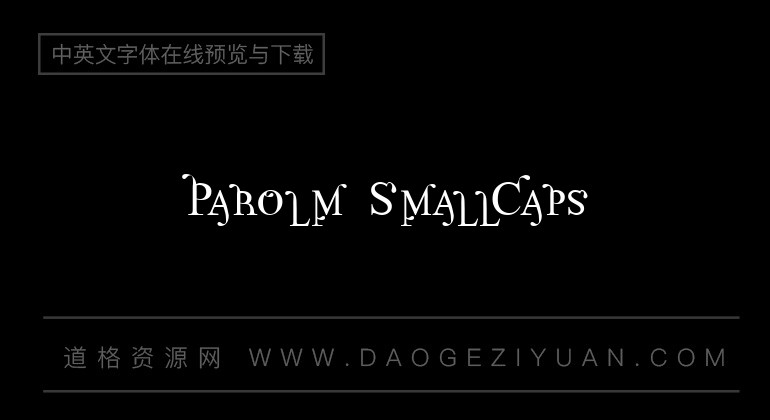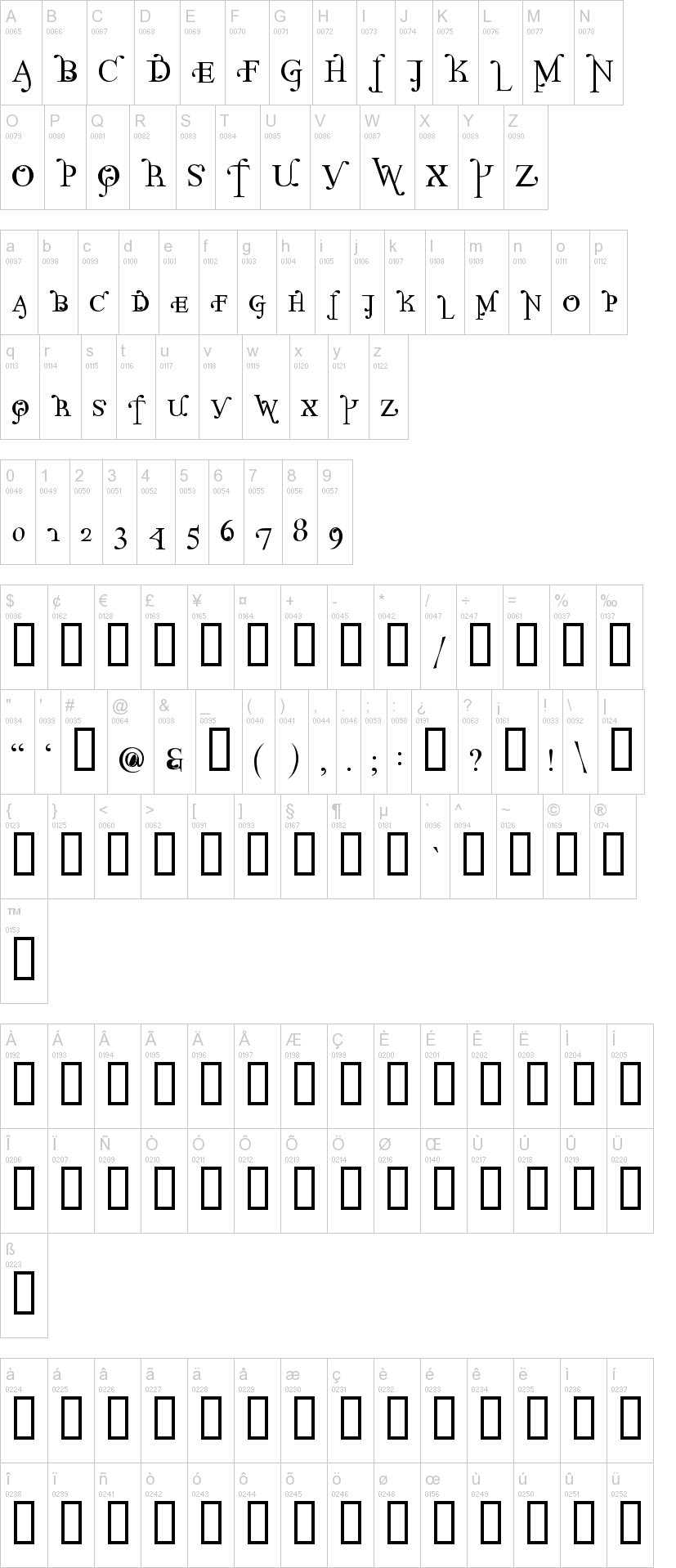
Parolm SmallCaps 是一款简洁优雅的小型大写字体,由 Parolm 公司设计和发布。它的设计灵感来自于经典的报纸字体,在现代化的设计中,它保留了传统的风格,同时具有更加现代的视觉效果。它的字形设计细腻,字重均匀,笔画细腻,给人一种清新舒适的感觉。Parolm SmallCaps 字体可以用于各种文字的设计,特别适用于标题、标签、报纸、杂志等文字的设计,可以给文字设计带来更多的视觉效果。内容介绍
Parolm SmallCaps是一款非常不错的手写艺术字体,具有很好的视觉感,适合于文化类的宣传设计、商业类品牌的广告和产品包装设计以及个性化文字排版等较多场景。